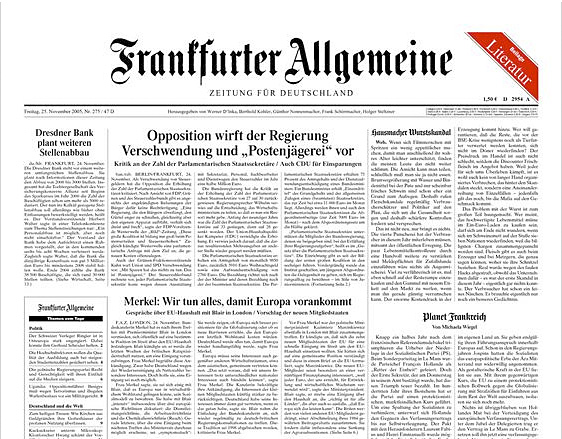
FAZ in neuem DesignHorizont meldet: »Die Frankfurter
Allgemeine Zeitung kommt ab kommender Woche in einem veränderten Design
und in überarbeiteter Struktur auf den Markt. Die bekannte Frakturschrift
in Titelkopf und den Kommentarüberschriften der FAZ bleibt jedoch ebenso
bestehen wie die Vorherrschaft der Textinformation.« Wir ahnen schon: viel
wird sich nicht verändern. Doch eines scheint mindestens so
revolutionär wie das Foto auf der Ausgabe vom 12. September 2001: die
Zusatzfarbe Rot im redaktionellen Teil der Titelseite wird
![]() FAZ-Mitherausgeber Werner D’Inka erläutert die signifikantesten
Änderungen: » ... eine leicht erhöhte* Grundschrift, etwas
vergrößerte und verschlankte Überschriften, eine
Zurücknahme der Spaltenlinien und das rote Faz.net-Logo auf der Titelseite.
Hervorstechendes Merkmal: das leicht ins Terrakotta spielende Rot, das sich als
Auszeichnungsfarbe bei Hervorhebungen in Kästen und den neuen seitlichen
wie den unteren Inhaltsleisten wiederfindet, dazu immer wieder mehrzeilige
Textfenster.«
Und jetzt kommt es ganz dicke: »Redaktionelle Sonderleistungen werden künftig auf der linken Spalte der Titelseite durch ein rot hinterlegtes Textfenster hervorgehoben.« (D’Inka) Das neue Layout wurde intern entwickelt. *wahrscheinlich ist »größere« gemeint; oder handelt es sich um einen Begriff aus dem Bleisatz? ![]() Treue FAZ-Leser sind bereits vorgewarnt: Zusatzfarbe Rot auf der ersten Seite ... demnächst auch im redaktionellen Teil Herausgegeben: Do - November 24, 2005 at 08:38 nachm. | |